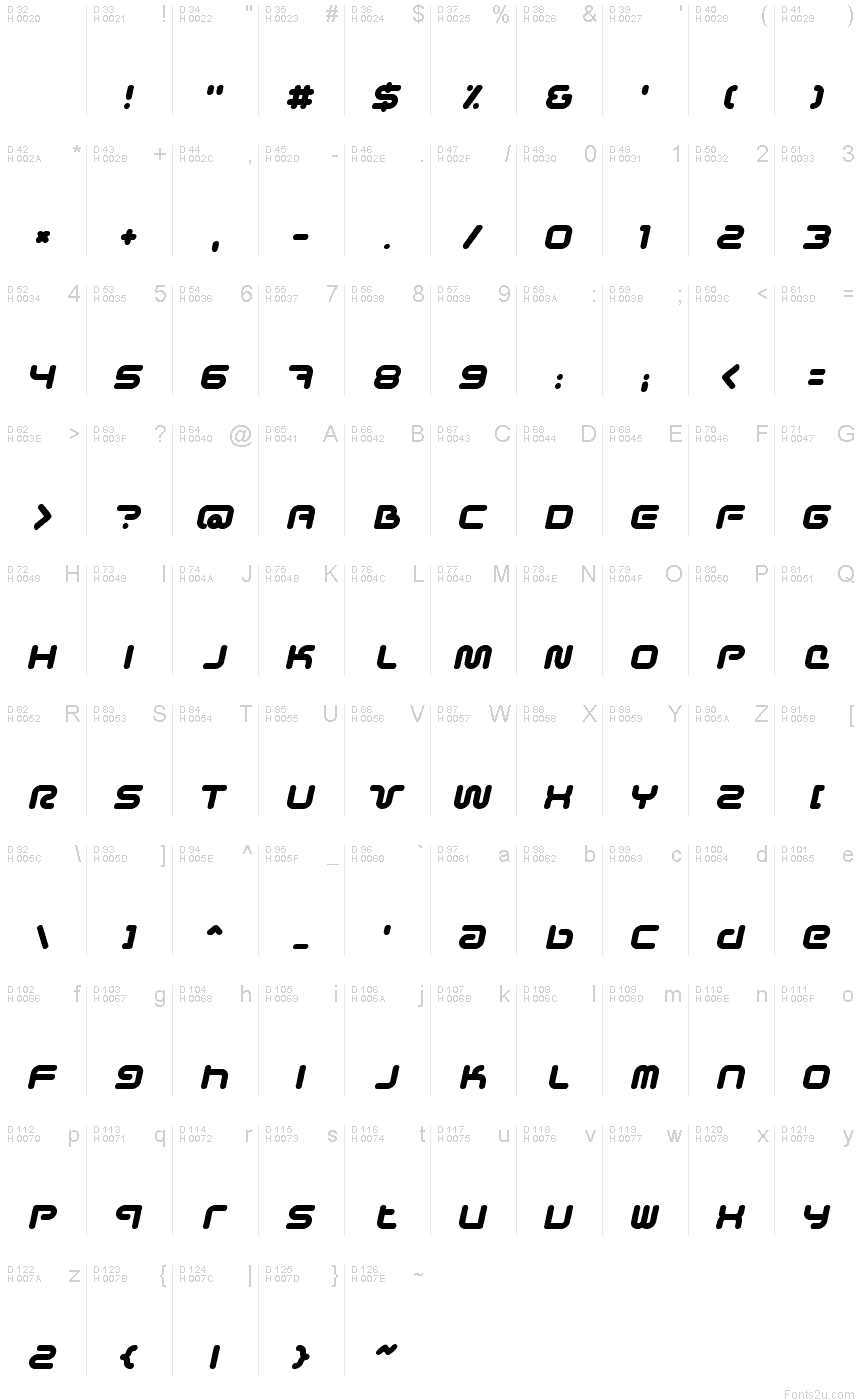
Sci Fied BoldItalic di dustBUST Fonts è un carattere display futuristico gratuito, caratterizzato da un'inclinazione veloce tipica della fantascienza. Le lettere sono costruite con tratti ampi e arrotondati e spazi vuoti stretti, che rendono la forma delle parole aerodinamica, quasi come la segnaletica di una sala giochi rétro, anziché un neutro sans serif moderno.
Si adatta perfettamente a loghi di giochi, titoli di poster, copertine di album, schermate di titoli e grafiche per eventi tecnologici, dove quella spinta in avanti conferisce movimento alle brevi frasi. Essendo un font gratuito, funziona bene anche per splash screen, sovrapposizioni di streaming e monogrammi, soprattutto quando si desidera che le maiuscole appaiano eleganti e leggermente cinematografiche.